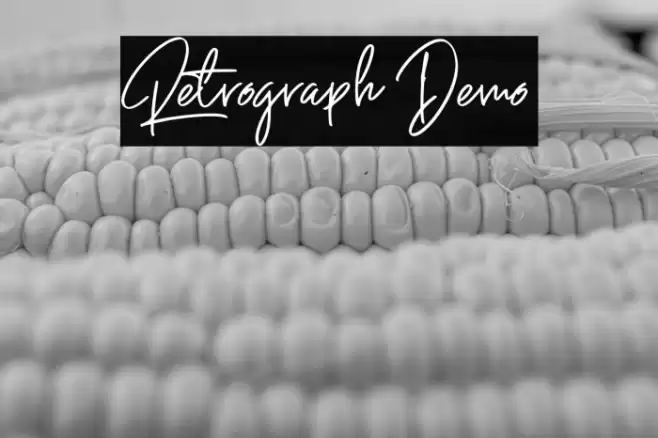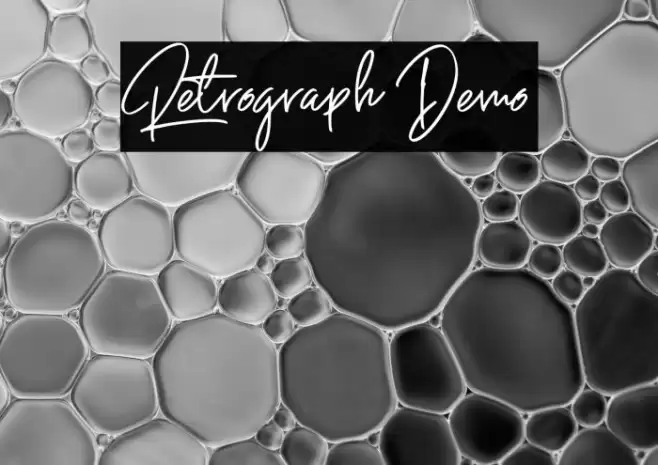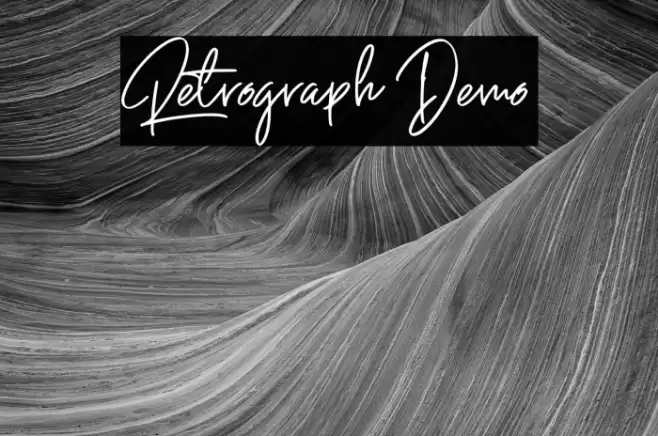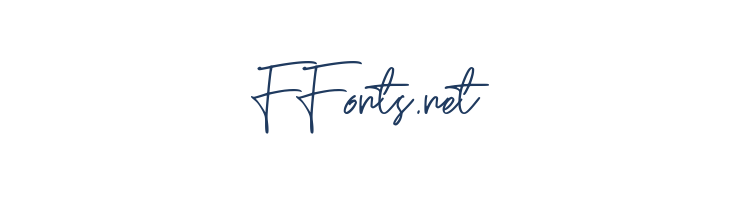
Retrograph Demo Font
| Estilo general | Vintage |
| Proyectos propuestos | Ideal for vintage-themed posters, retro branding, nostalgic advertisements, and creative design projects that require a touch of the past. |